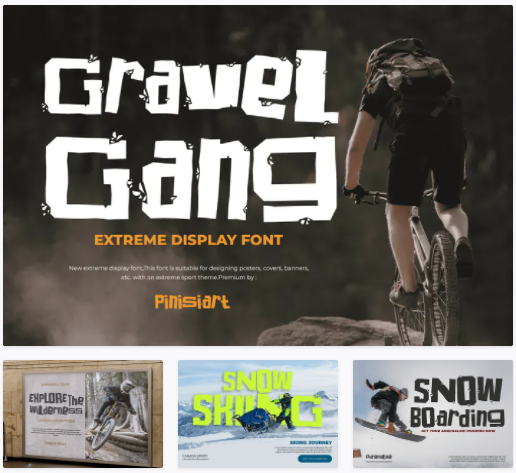
Gravel Gang - спортивный шрифт!
Звуки слюны, звук скрежета гравийной дороги, раздавливаемой велосипедом. Это то, что нужно миру экстремального спорта.
Отлично подходит для онлайн-игр, плакатов, названий фильмов, меню фастфуда, журналов, обложек youtube, миниатюр youtube, обложек страниц социальных сетей и так далее...